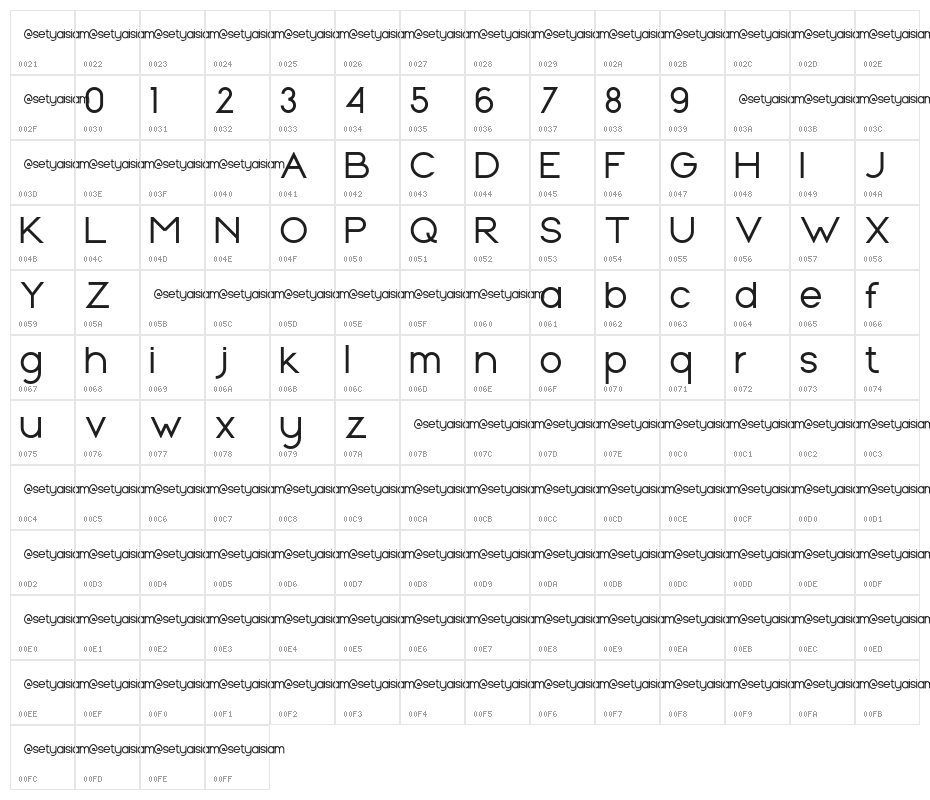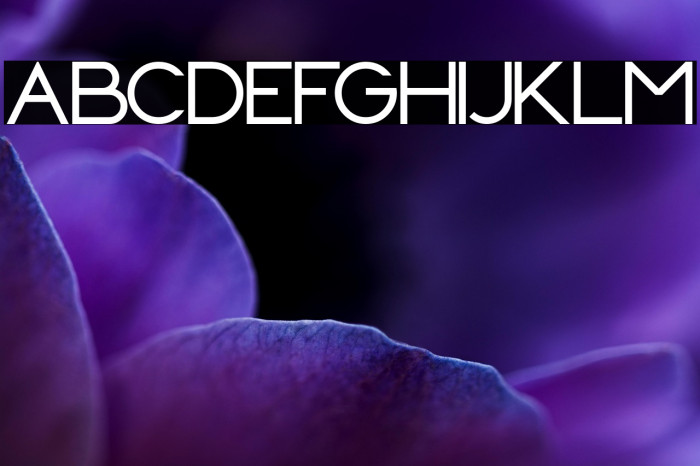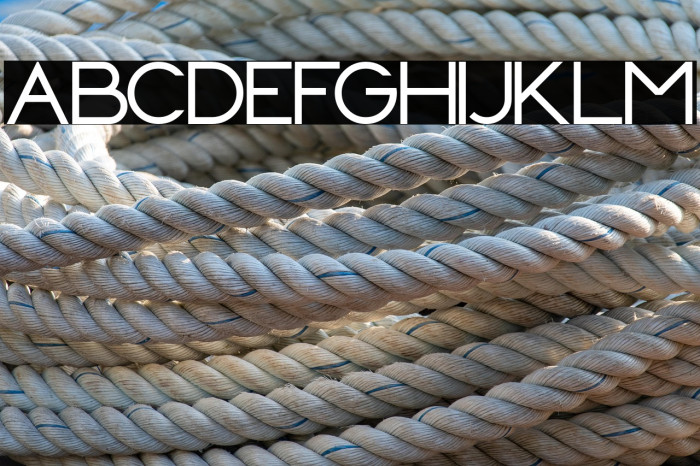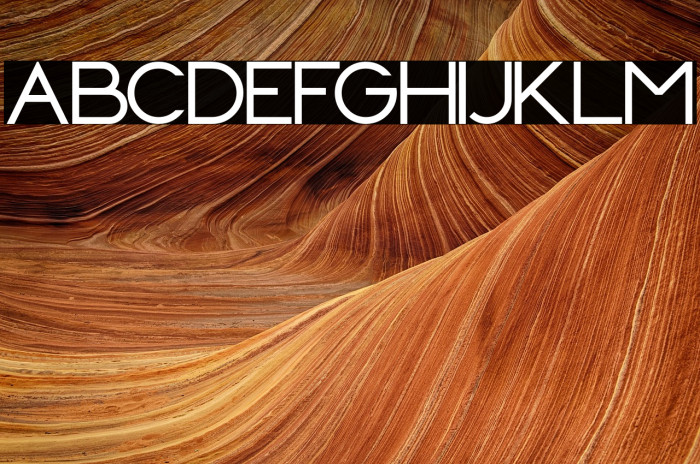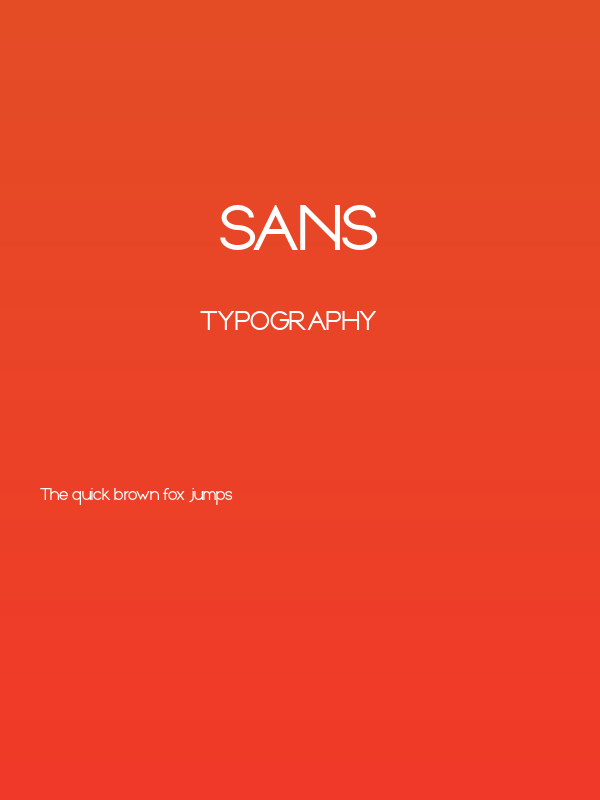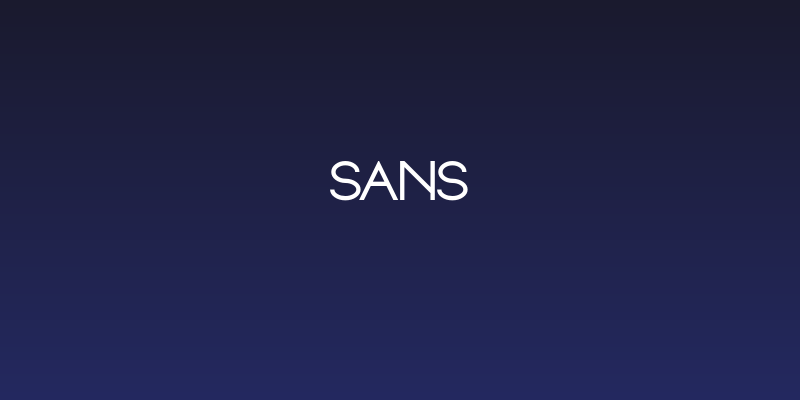
sans Font
✎ Sans Serif
| Kategorien | Sans Serif |
| Anwendungsfall | Headlines, Body text, Logos |
| Vorgeschlagene Projekte | Ideal for branding, web design, corporate materials, and editorial layouts due to its clarity and modern appeal. |